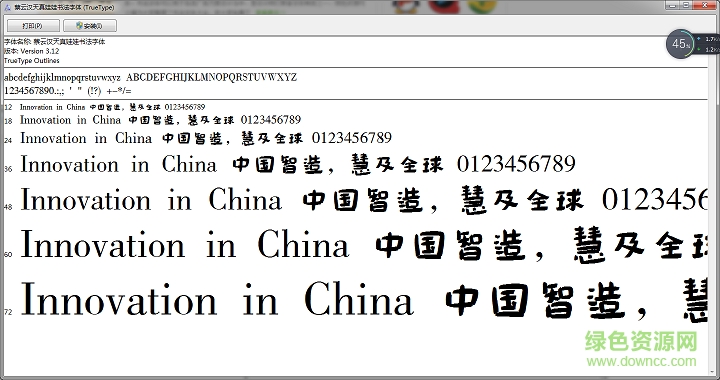
蔡云漢天真娃娃字體
蔡云漢天真娃娃書法字體是作者根據(jù)王憨山先生書體和古碑《廣開土王境平安好大王碑》格調(diào)而作。又融合了現(xiàn)代的卡通書體的風(fēng)格。是一款融合了現(xiàn)代卡通書體風(fēng)格的中文漢字,非常的漂亮唯美,適用于平面設(shè)計、廣告創(chuàng)意、兒童畫報等行業(yè),喜歡的朋友不要錯過啦。
蔡云漢天真娃娃書法字體